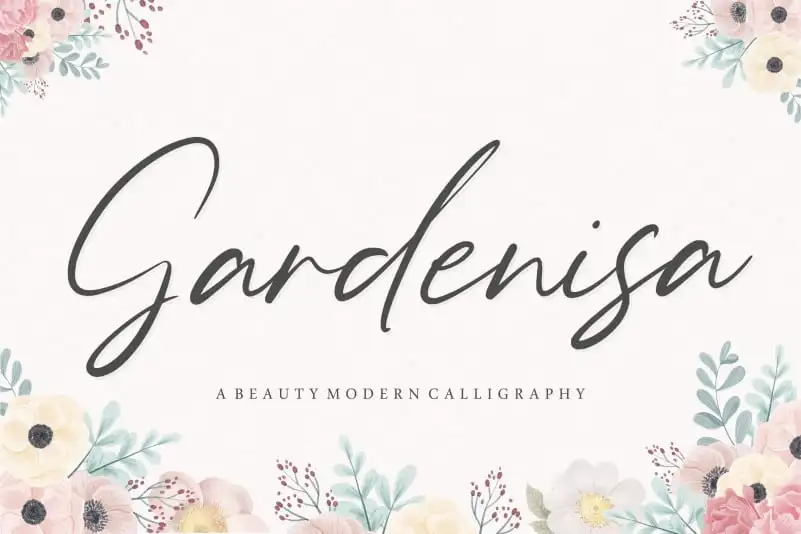
Gardenisa Beauty Calligraphy Font – Download Grátis
A Gardenisa Beauty Calligraphy Font é perfeita para criar trabalhos profissionais com estilo, especialmente ideal para aplicar na embalagem de produtos, no projeto de marca e até mesmo nas redes sociais. Seu traçado elegante e refinado permite que suas ideias sejam transmitidas com clareza e atração. Esta fonte é um ótimo complemento para qualquer projeto que exija uma escrita bonita e envolvente. Perfeito para editoriais de revistas, criações para eventos como casamentos ou até mesmo simplesmente para destacar frases em fundos mais básicos. Sua capacidade única permite que as palavras se destacuem, tornando-a uma escolha conveniente para designers que desejam um efeito sofisticado em suas criações.